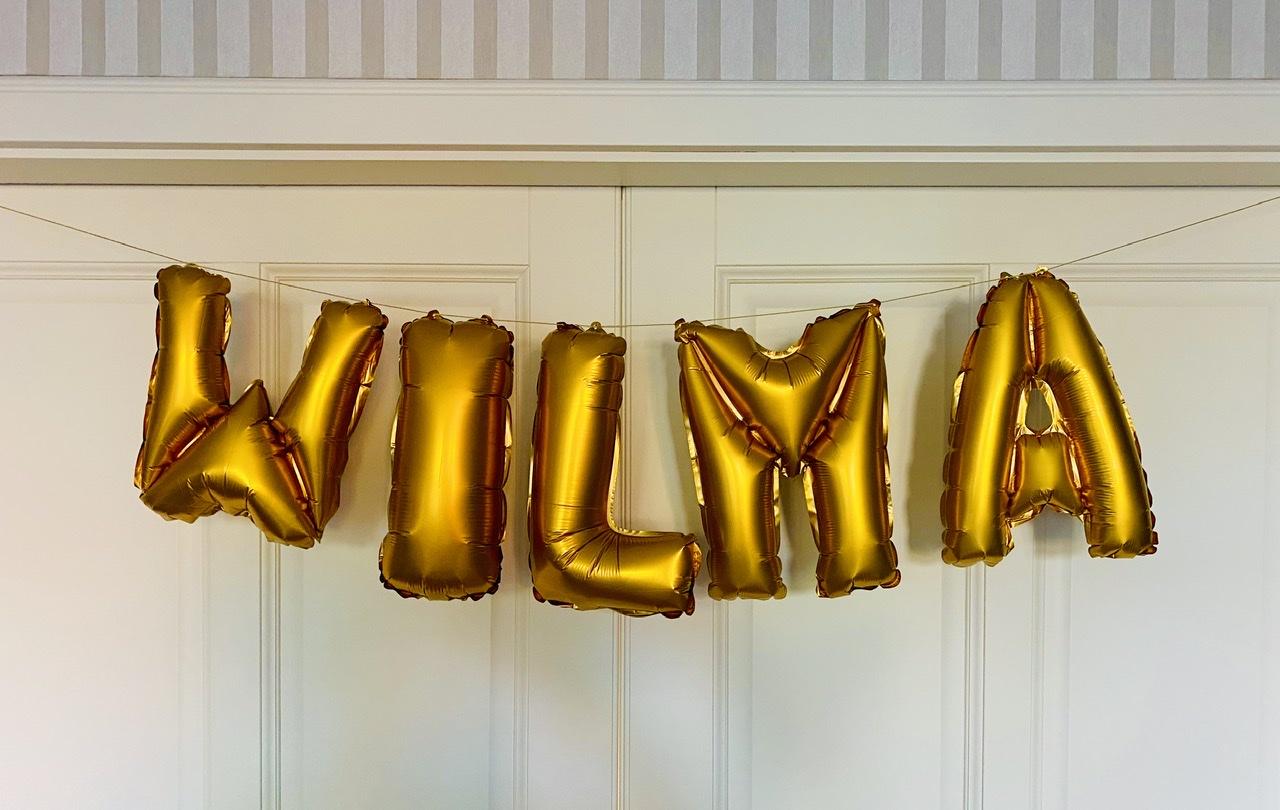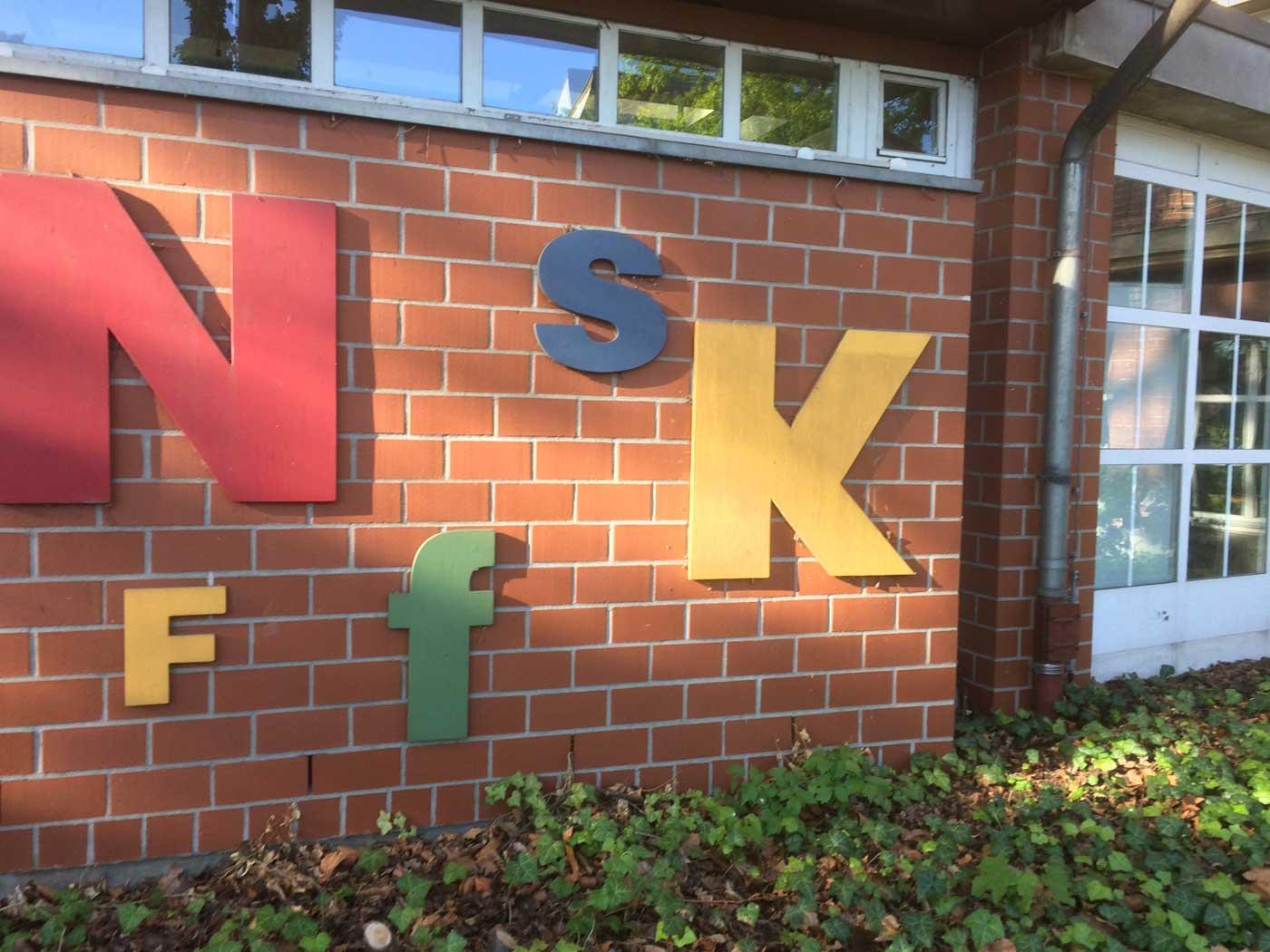
Dann ist die Idee mit den Variable Fonts ja nicht so neu wie ich dachte … coole Konzepte jedenfalls!
Was bedeutet „Überfüller“ in diesem Zusammenhang? ...
Überfüller: Über den Rand hinaus vergrößerte Druckpläche einer über eine andere Farbe grdrückte Farbe, um hier durch mangelhafte Passerhaltigkeit entstehenden Versatz Blitzer zu vermeiden.
Das war ein typisches "Design" Element der flächigen Flexidruck-Etiketten der DDR, und gab ihnen eigentlich einen ganz speziellen Charme. Auch ich fand dieses, durch die Zwänge der technisch eingeschrämkten Drucktechnik entstehenden Etikettenentwürfe eigentlich doch recht schön.
Ich habe diesen Effekt ja beim Nachbau des Etiketts für das Illustrationsbild auch nachgestellt:
Helga?
Alice?
Elke?
Claudia?
Gwendoline?
Tante Edith hat die Kopf-Stereoanlage aufgedreht und kopfnick0rt so vor sich hin
Kindergeburtstag! :schonklar:
Das »I« scheint ein fetterer Schnitt zu sein.
Uuuh, ich sehe faces in places -- ein Fuchsluchs im M:biglove:
Soll ich dir sagen wie Wilmas Schwester heißt? Dann hast du direkt was anderes im Ohr ...
Olivia :-?:hammer:
Keiner schmettert die Biene-Maja-Hymne besser als Karel Gott :rockon:
R.I.P. :-(
Wir sind dem Trickfilm-Genre treu geblieben ... :-?
Da ging ich von aus …
Ein typografisches Fundstück im weitesten Sinne …
Ich war ja irgendwie mehr bei Musik 🙂
Ein eher düsteres Kapitel der B-52’s ... :shock:
düsteres Kapitel
Ja, das stimmt. Aber es hat mich zu den Ärzten gebracht (siehe die Namen, die nach Wilma durch meinen mentalen Konzertsaal hallten).
Höre ich heute noch gerne.
Da wir zuhause erst mit meinem ersten Mac auch einen Fernseher bekamen, sind mir diese ganzen Trickfilme eigentlich fremd. Welche Serie ist das? Ich glaube, ich hab die Realverfilmung mal gesehen, kann mich aber überhaupt nicht an den Titel erinnern...